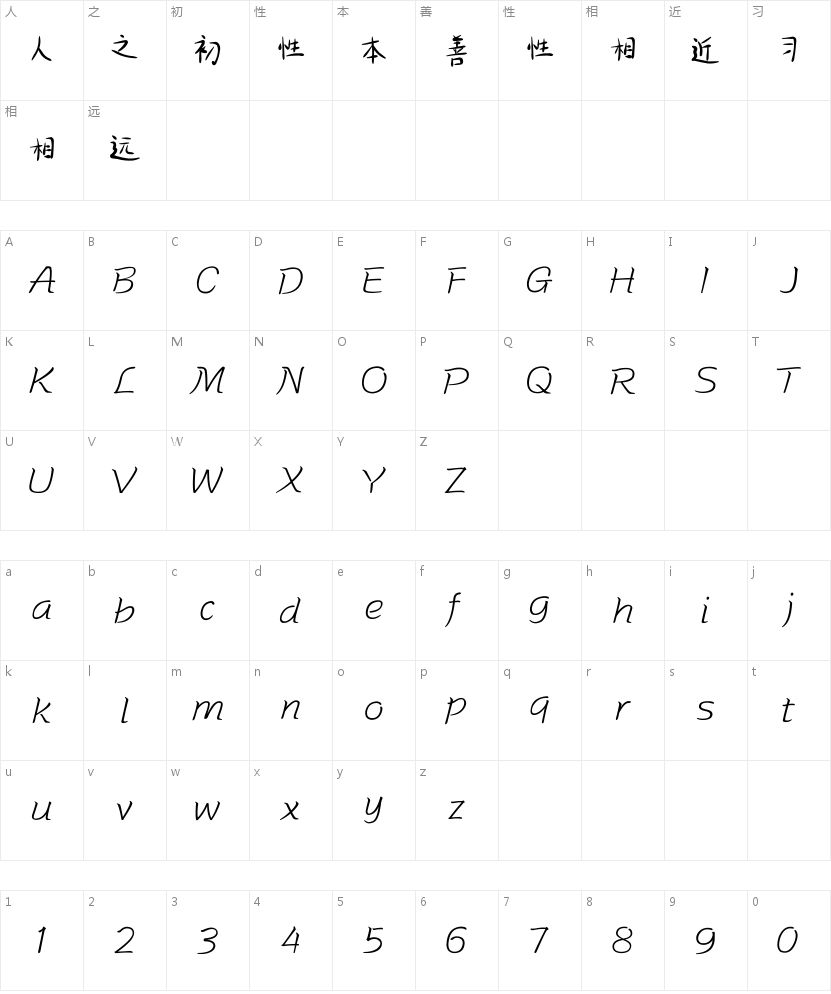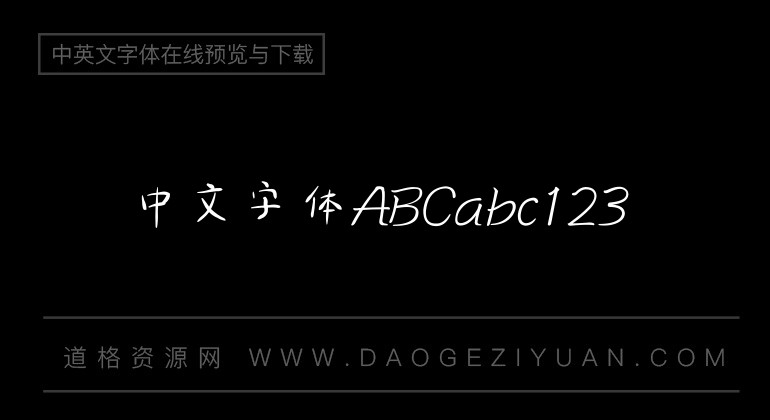
王强手写
王强手写字体是一种具有个性化特点的书写风格,它源于中国书法艺术中的行草字体。王强手写字体通常具有横平竖直的直线和圆弧相结合的曲线,线条粗细、长短、起伏有别,显现出一种自由、狂放、有力、豁达的艺术感。其特点是笔画粗劲有力、气势磅礴、结构简洁、形态独特,表现出了一种独特的个性和艺术风格。 王强手写字体广泛应用于书法、设计、广告、标志、海报等领域,成为一种独具特色的艺术表现形式。很多人也会将王强手写字体应用于自己的签名和日常书写中,以表达自己的个性和独特风格。
王强手写是一款非常不错的手写艺术字体,具有很好的视觉感,适合于文化类的宣传设计、商业类品牌的广告和产品包装设计以及个性化文字排版等较多场景。
王强手写字符映射图